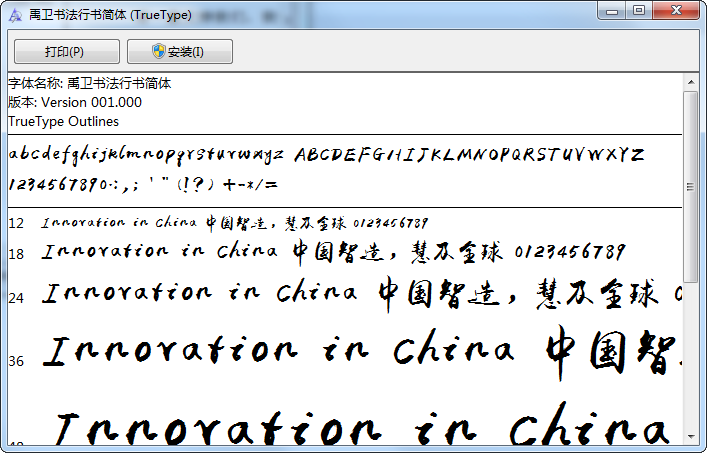
yuweij字體 禹衛(wèi)簡(jiǎn)
yuweij字體是禹衛(wèi)字體中的一種,也叫禹衛(wèi)行書簡(jiǎn)體,這款字體字形飄逸俊朗,感興趣的朋友趕緊來(lái)綠色資源網(wǎng)下載體驗(yàn)吧!
yuweij字體介紹
禹衛(wèi)書法行書簡(jiǎn)體是一款以毛筆行書書為主的GB_2312字庫(kù),這里包含了常用字和生僻字共6763個(gè),可廣泛適用于微軟office的各種軟件、qq、MSN等常用聊天工具、photoshop等主流繪圖軟件